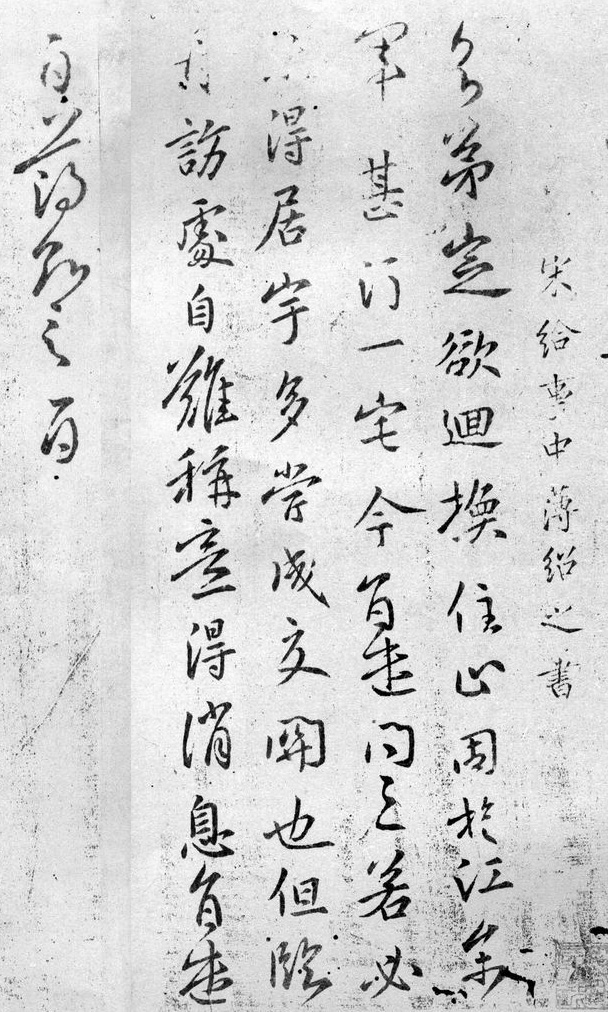
薄绍之
薄绍之简介
南朝宋人薄绍之,丹阳人,字敬叔。官至给事中。善书,风格秀异。尤工行、草,行草倜傥,时越羊欣。
梁代学者袁昂作《古今书评》,称“薄绍之书,字势蹉跎,如舞女低腰,仙人啸树,乃至挥豪振纸,有疾闪飞动之势。”(《太平御览》卷七四八)。梁武帝萧衍《古今书人优劣评》称“薄绍之书如龙游在霄,缱绻可爱”。庾肩吾《书品》列其书为下之上品,张怀瓘《书断》卷中列其隶书、行书、草书入妙品。古人有赞:“师法小王,风格秀异,若干将出匣,光芒射人,魏武临戎,纵横制敌”。
选自大观帖